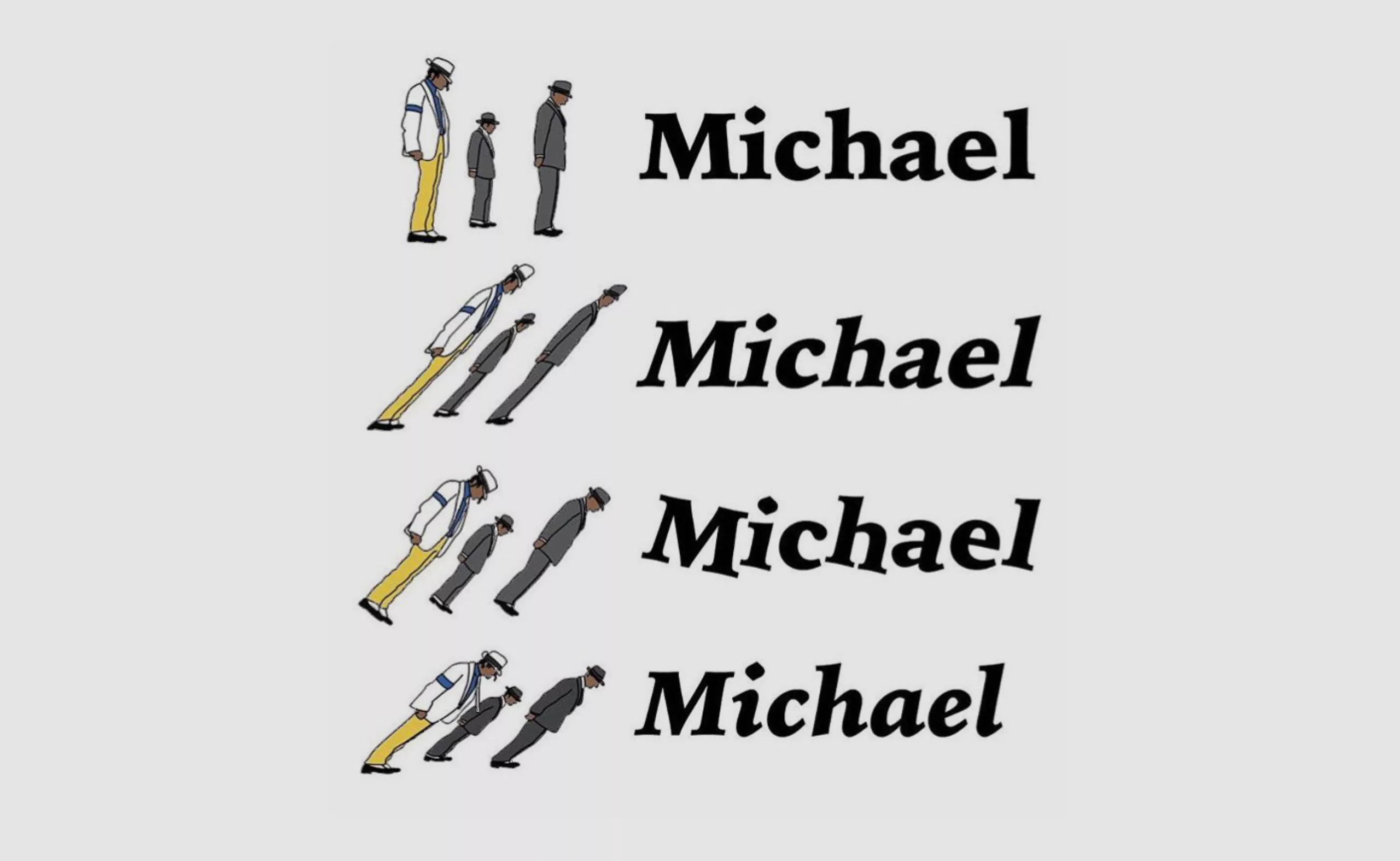
Un cours de typographie avec Michael Jackson !
Oblique ou Italique ?
En opposition au romain, l’italique est l’inclinaison du texte vers la droite. En principe, il s’agit d’une fonte particulière (italique cursif) dont chaque caractère a été pensé par son créateur. En effet, les œils * de l’italique ne sont pas simplement des variantes obliques des lettres romaines. Ils sont plus cursifs, plus gestuels que ceux des lettres romaines.
Souvent, en l’absence de cette police, le romain est mis en italique automatiquement, subissant une distorsion forcée par le logiciel (italique penché).
* Il ne s’agit pas d’une faute d’orthographe ! Sachez qu’il s’agit d’un pluriel spécifique au jargon de la typographie !
Petite histoire de l’italique !
L’écriture italique a été inventée en 1499 par Francesco Griffo, en réponse à la demande d’Alde Manuce, qui en bon capitaine d’imprimerie, souhaitait diminuer la taille de ses ouvrages, afin d’en réduire les coûts et ainsi en faciliter l’accès aux étudiants. En gros c’était un peu une sorte de réduction spéciale 12/25 !
Initialement appelés « lettres vénitiennes », ces caractères penchés seront rapidement nommées « italiques » en raison de leur origine italienne.